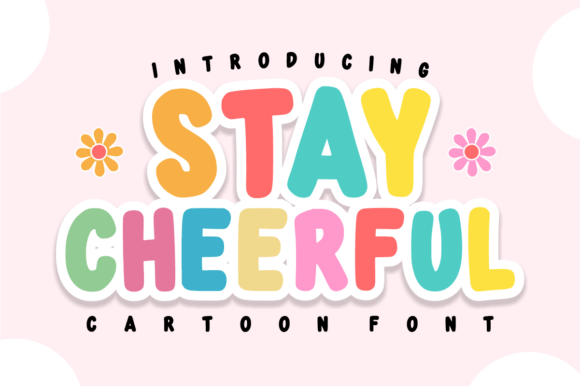
Stay Cheerful
適切なデザイン要素を見つけるのは難しい場合がありますが、Stay Cheerfulは作品を即座に引き立てる優れたコレクションを提供します。
POD(オンデマンド印刷)製品、結婚式の招待状、またはソーシャルメディアのグラフィックを作成している場合でも、Stay Cheerfulは理想的です。